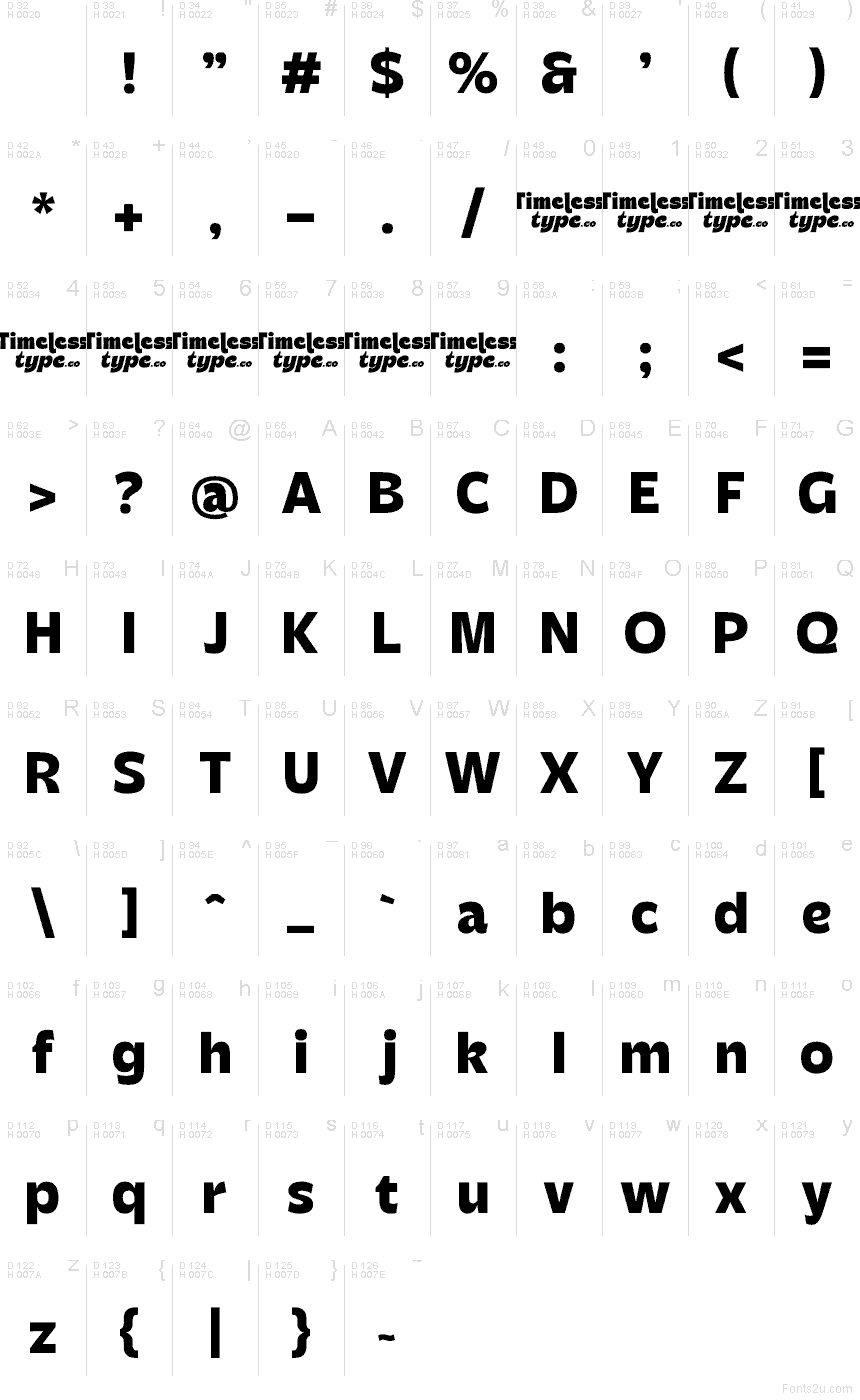
Seatren von TimelessType.co ist eine kostenlose serifenlose Schrift mit weichen Kanten, die massig und entspannt wirkt. Die Buchstaben sind zugleich breit und kompakt gestaltet – mit kräftigen Kurven, stumpfen Enden und einer leichten Dynamik, die verhindert, dass der kräftige Stil steif wirkt.
Sie eignet sich hervorragend für Plakat-Überschriften, Branding für Cafés oder Streetwear, Verpackungen, Social-Media-Grafiken und kurze Headlines, bei denen eine kostenlose Schrift Wärme statt Perfektion vermitteln soll. Da die Formen so dicht und abgerundet sind, funktioniert sie auch bestens für Titelkarten und schnelle Logo-Entwürfe, die einen freundlichen, soliden Schriftblock benötigen.